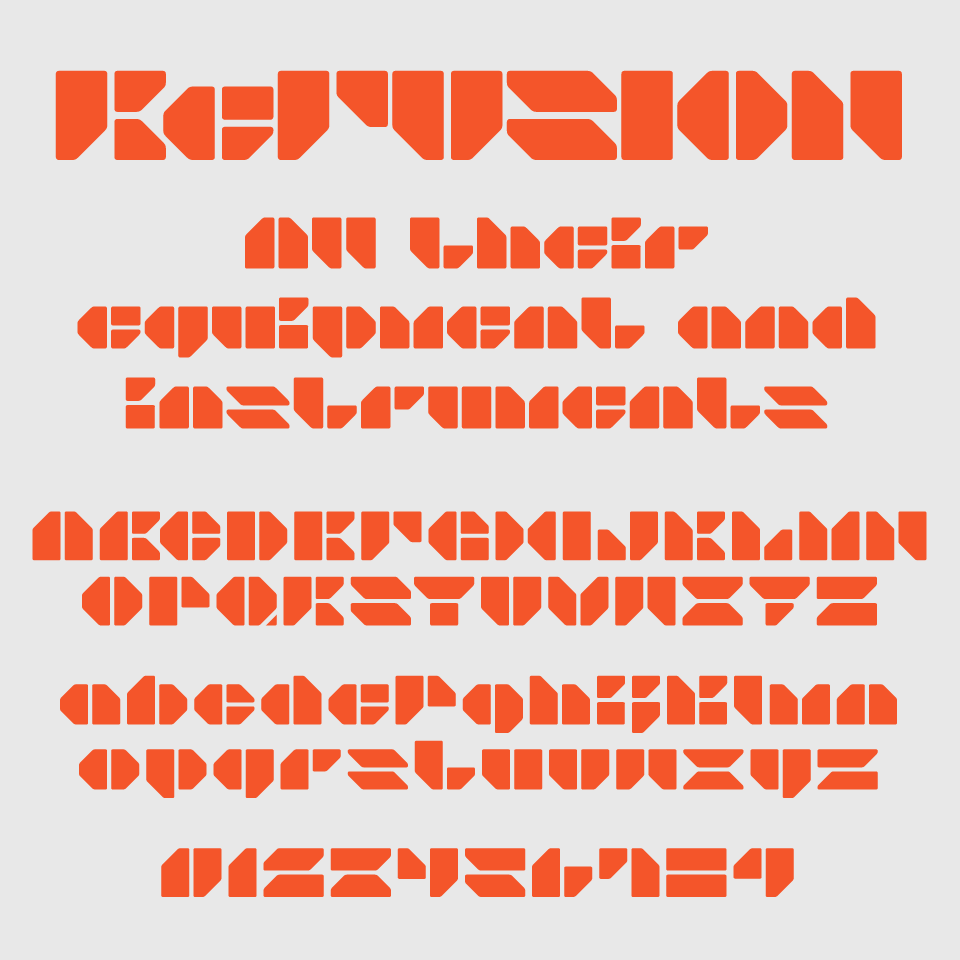
ReFUSIONフォントは、大きく塗りつぶされた幾何学ブロックを組み合わせて構成された、抽象的で実験的でカッコいいスタイルのフォントです。
視認性を一旦手放し、「読ませる」より「見せる」ことに特化したアプローチが印象的なデザインです。大きな図形を作っていることで、まるで建築模型並べたようなデザインで、設計図のような無機的美しさのあるフォントです。
e-SportsやSFやテクノロジー、アート系プロジェクトに特に相性が良く、情報を伝えるというよりは、世界観を「構築」するような使い方が似合うフォントです。